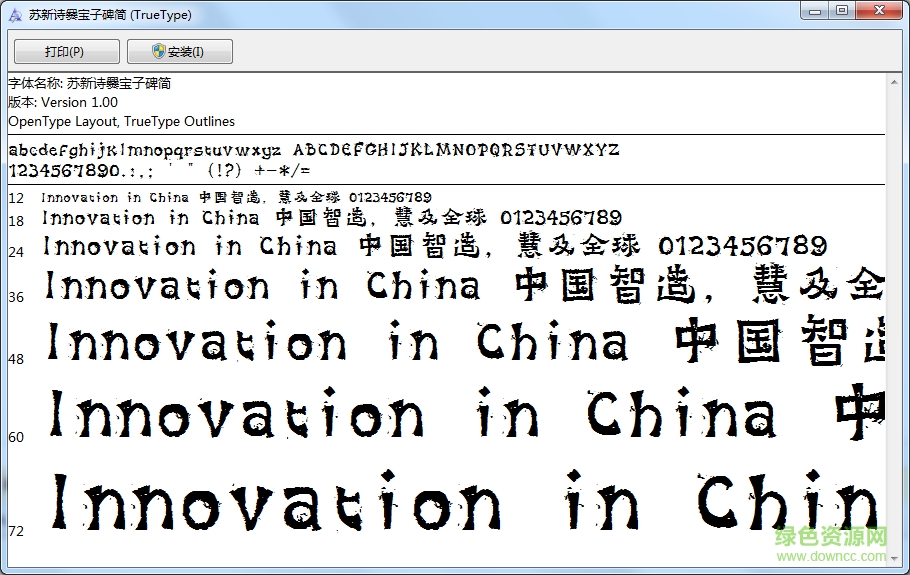
蘇新詩爨寶子碑簡體
蘇新詩爨寶子碑簡是一款簡體藝術(shù)字,文字以碑體為主,富有濃烈的碑體刻字感,字體周圍略帶點綴,少了一些正式感,顯得字體略帶休閑意味,歡迎有需要的朋友到綠色資源網(wǎng)下載使用!
應(yīng)用于書法方面的簡體中文漢字,該字體以碑體為原形,筆鋒犀利,字形大小適中,并且字庫完整,整體效果十分出眾,可用于卡通設(shè)計、廣告設(shè)計、平面設(shè)計、印刷包裝、報紙雜志等行業(yè)。